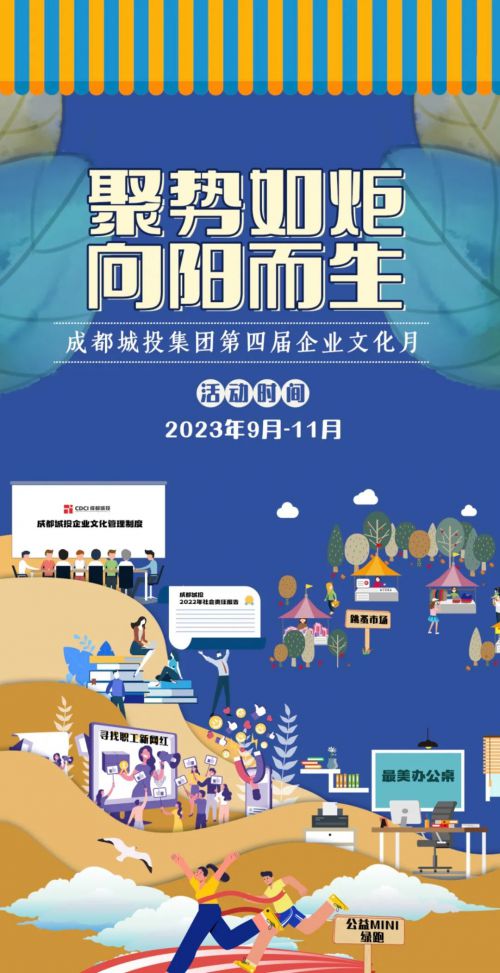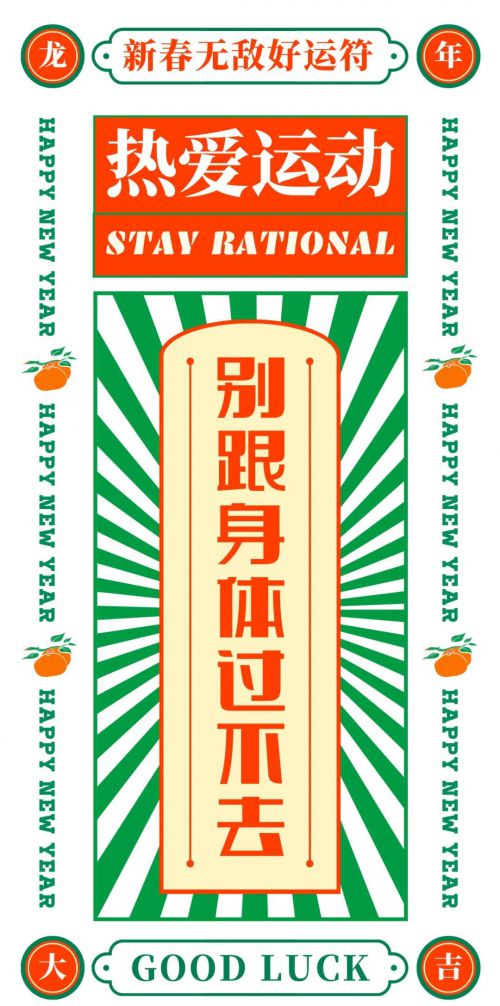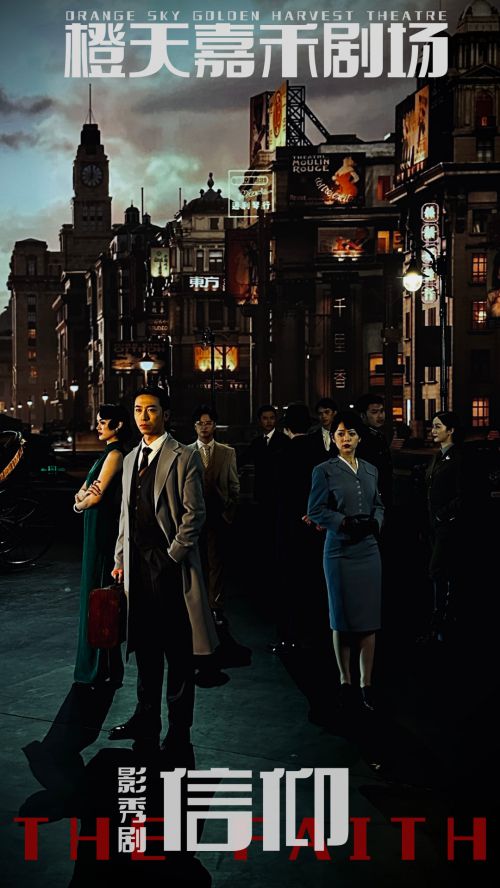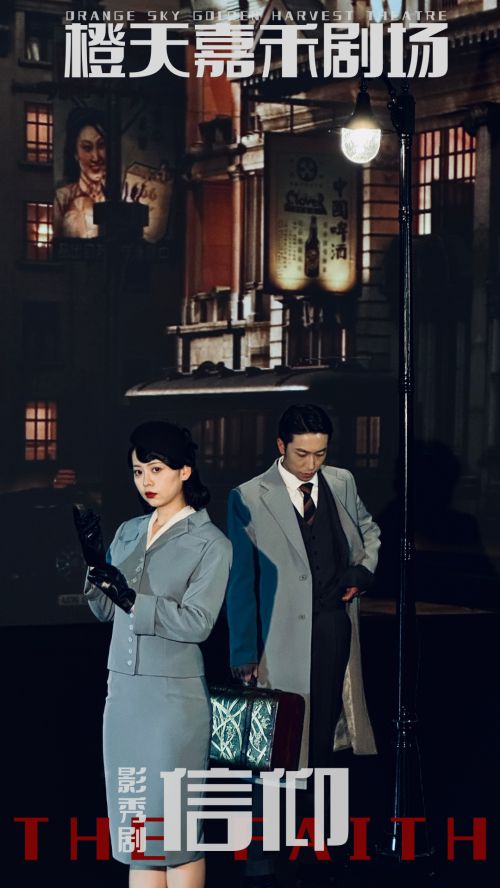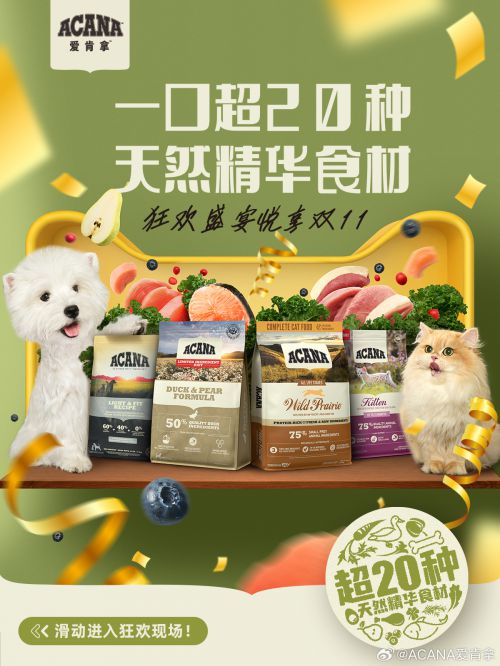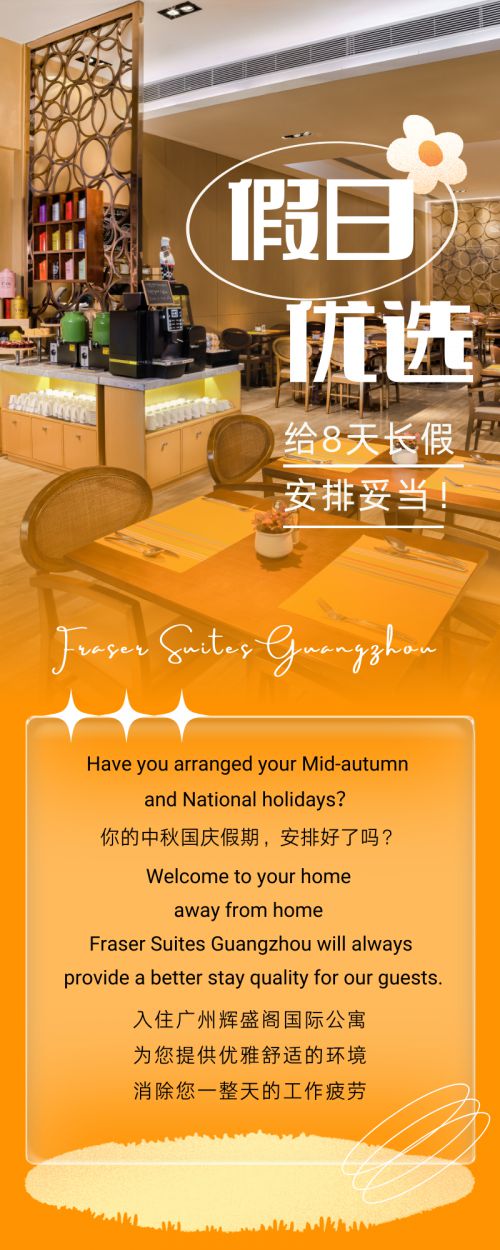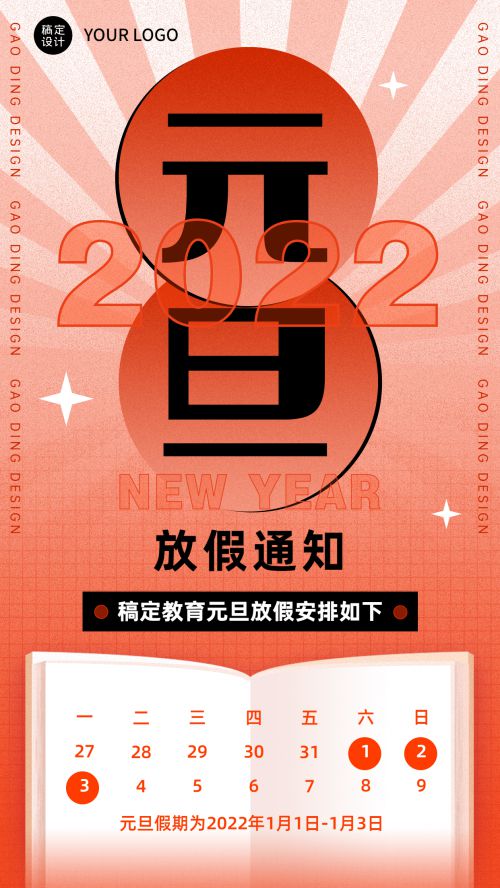
点字大字报
点字大字报融合民国美术字笔形特征,将单个字形的粗细对比变化夸张放大,从而营造出独有的美术字趣味,字面整体方正饱满,圆角与直角的结合,柔和中又填入少许刚毅。点字大字报字形力量感突出,视觉冲击力强,节奏明朗,充满艺术张力。
卢鑫亚
90后字体设计师,曾获第二届字体之星评委奖,最具商业潜力奖,第三届字体之星评委奖。